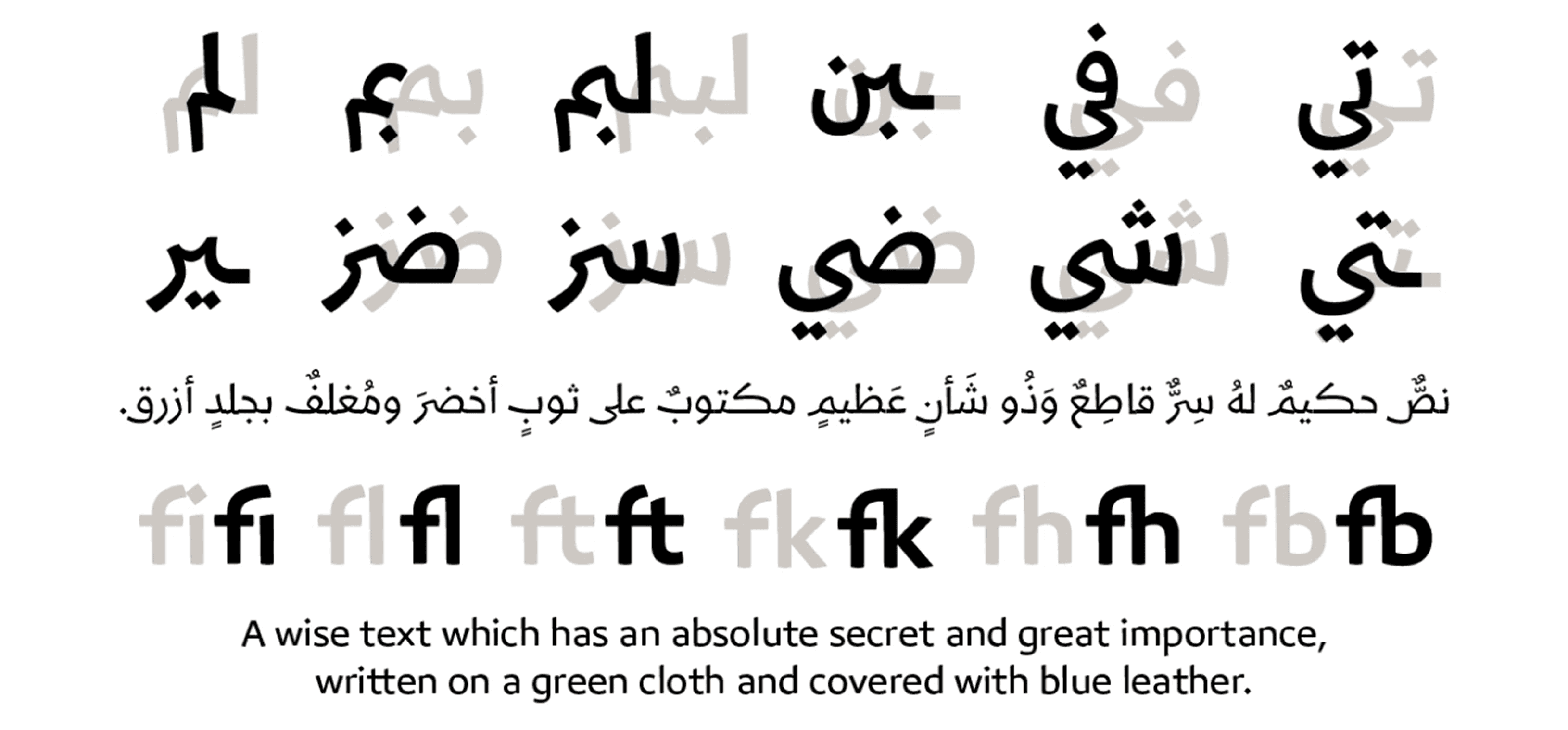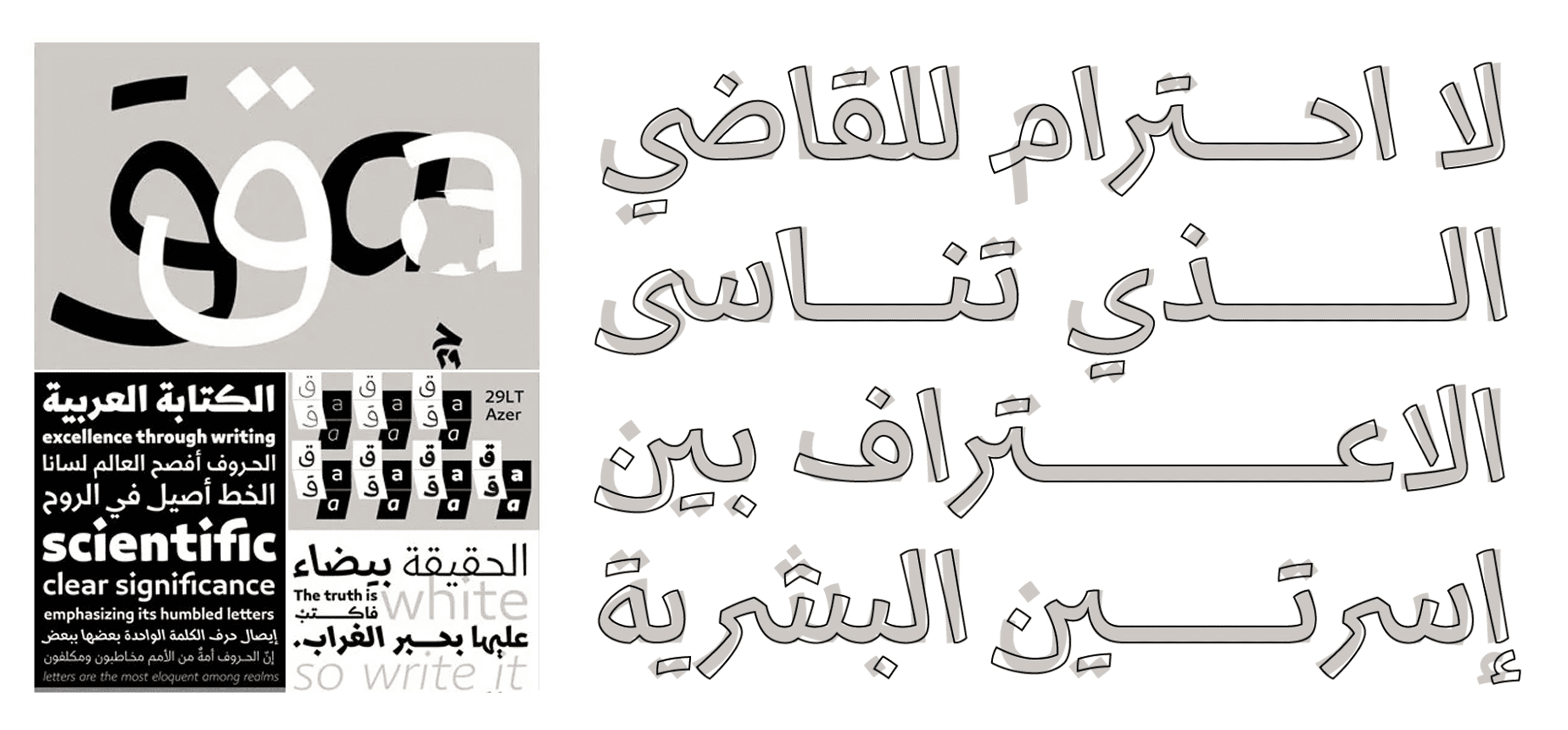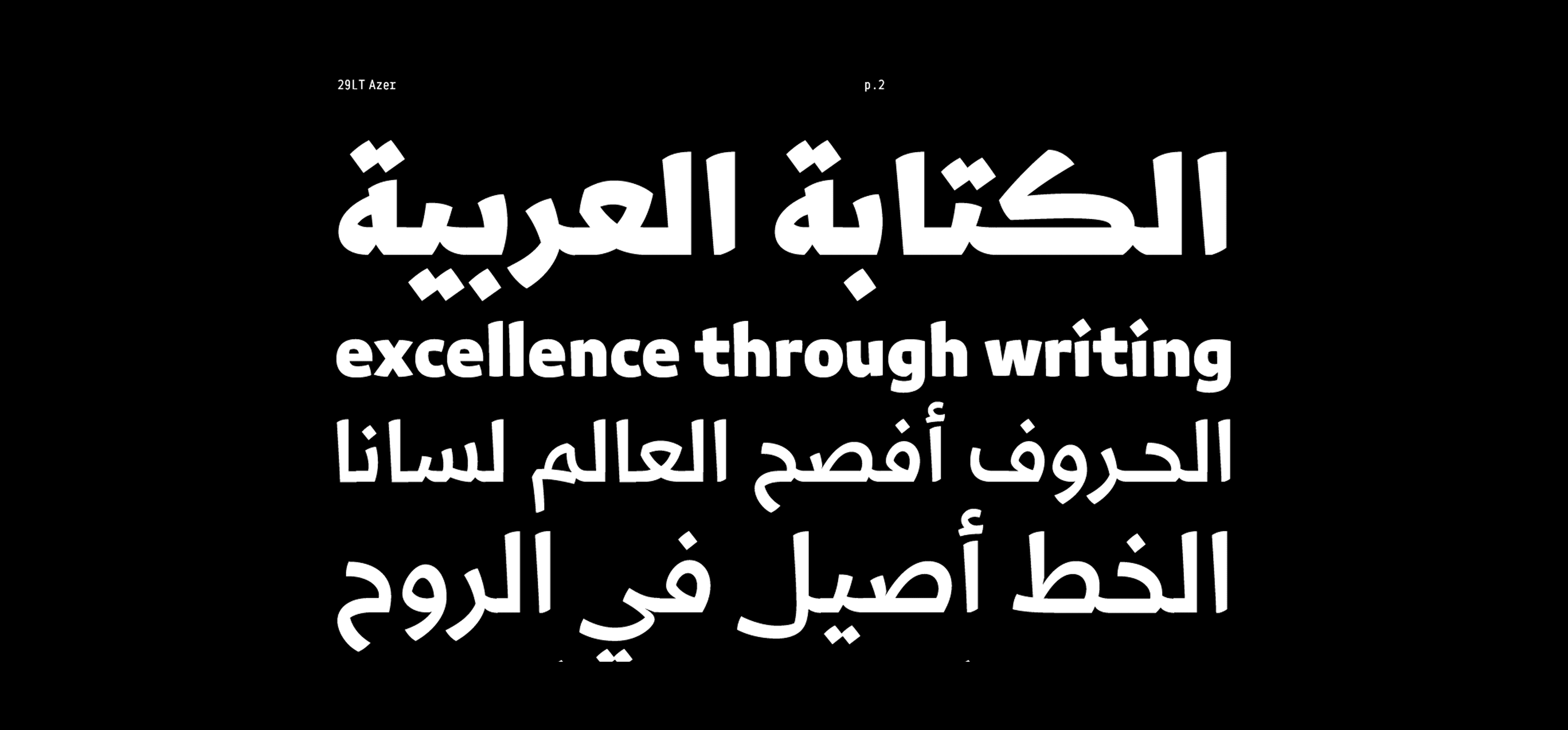
يمزج 29LT Azer بين الحداثة والدقة العلمية مع الأصالة العربية، مما يجعله مثاليًا للعناوين والنصوص التوضيحية. يتميز الخط بوضوح أحرفه، وتوازن بصري يجعله سهل القراءة ويمنحه طابعًا احترافيًا قويًا.